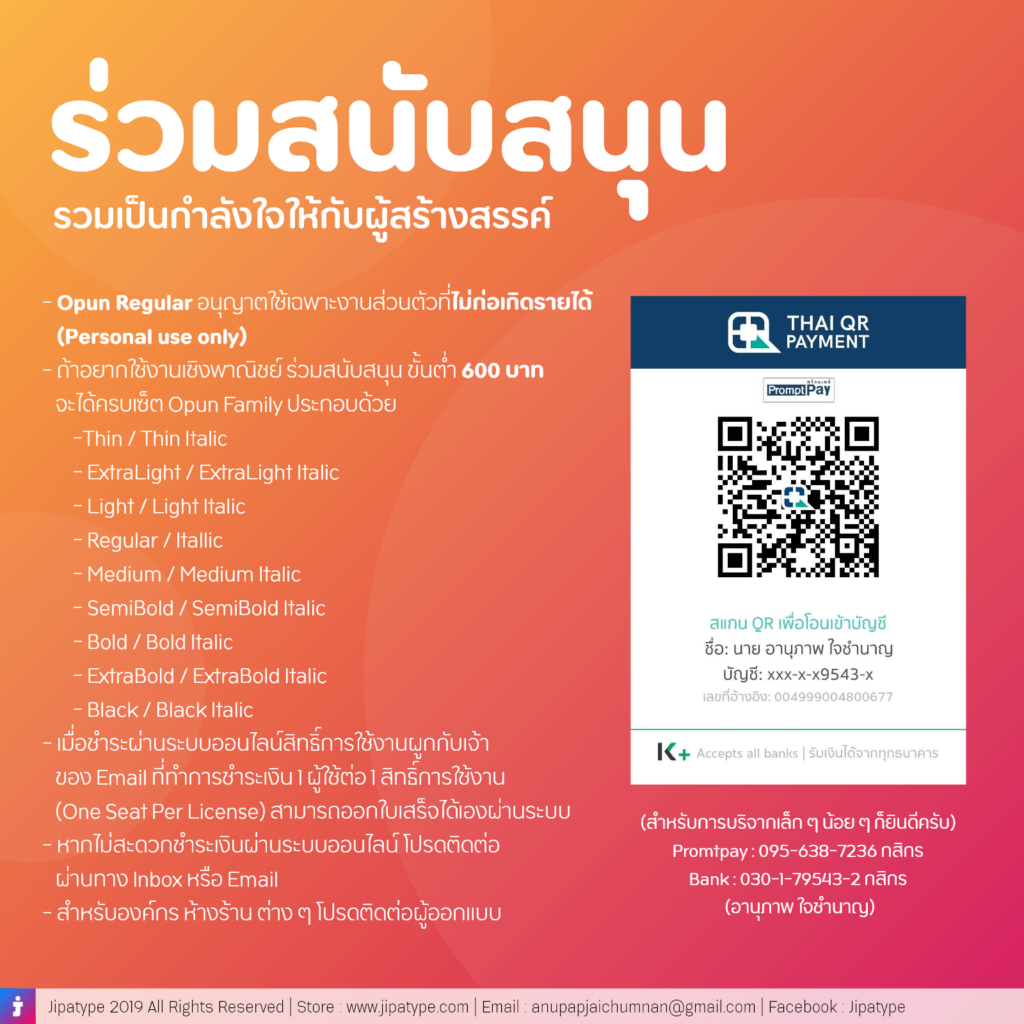
ฟอนต์ อบอุ่น ออกแบบให้มีความมนกลมเป็นมิตรต่อผู้พบเห็น เหมาะกับงานที่ต้องการให้ภาพลักษ์ของความอบอุ่น เป็นมิตร เช่น งานเกี่ยวข้องกับเด็ก ครอบครัว ความรัก ฯลฯ
ออกแบบโดย : อานุภาพ ใจชำนาญ (Anupap Jaichumnan)